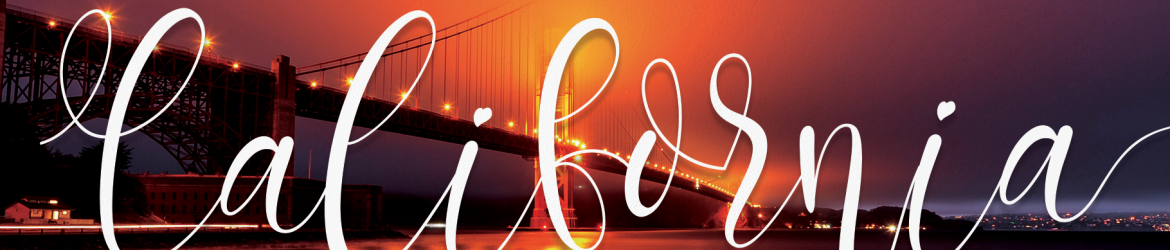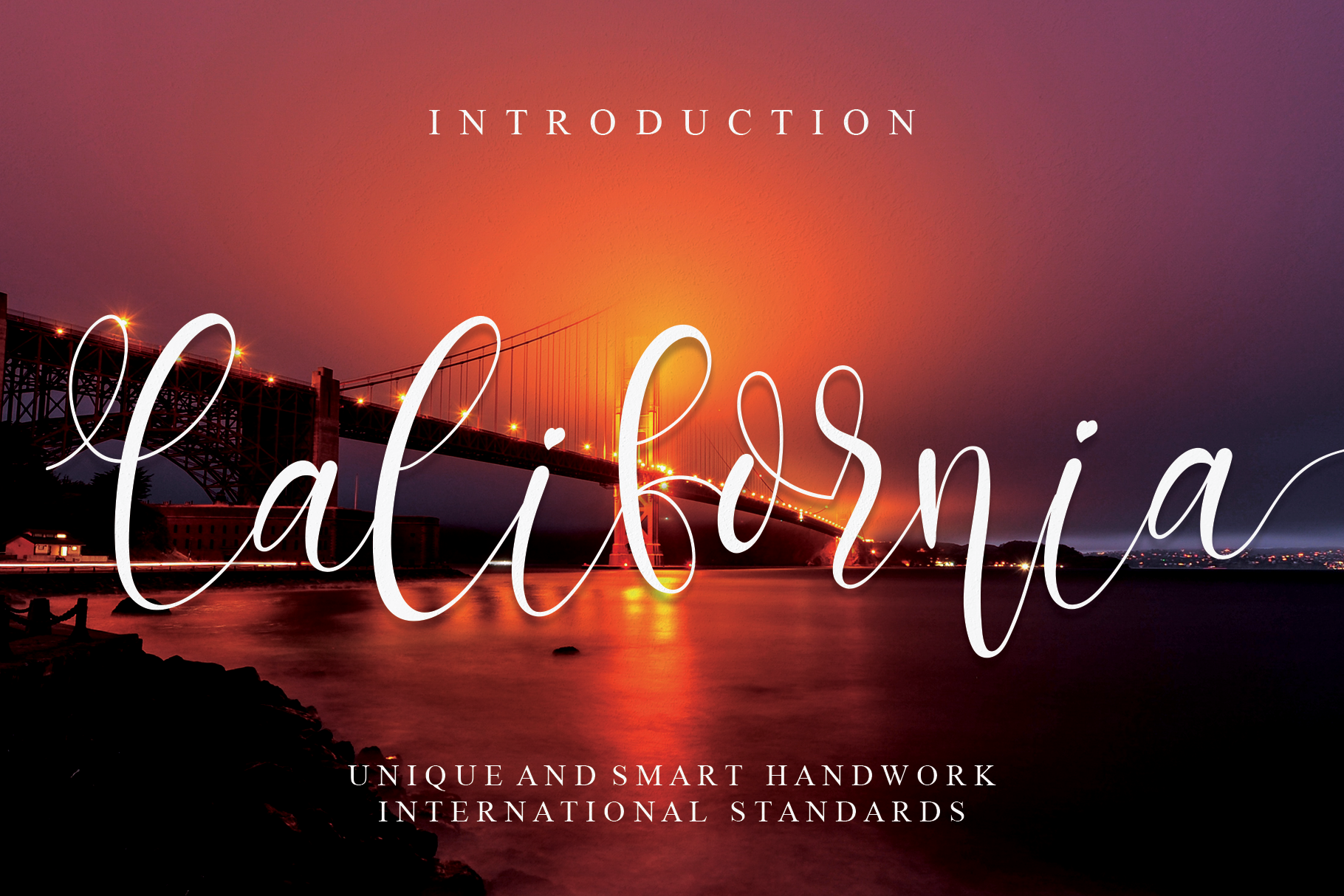
California Calligraphy Font
A California Calligraphy Font é a escolha perfeita para quem deseja adicionar uma graça elegante à sua identidade visual. Feita especialmente para produtores criativos, essa fonte oferece uma experiência única e extraordinária. Suas letras mais atuais são perfeitamente adaptadas para uso em displays de parede, convites de casamento, logotipos de redes sociais, anúncios, embalagens de produtos, designs de produtos, rótulos, fotografias, marcas, convites e papelaria. Ideal para qualquer projeto que precise de escrita a mão com um toque sofisticado. Com sua California Calligraphy Font, você pode transformar pequenos detalhes em um arco-íris de experiências criativas.